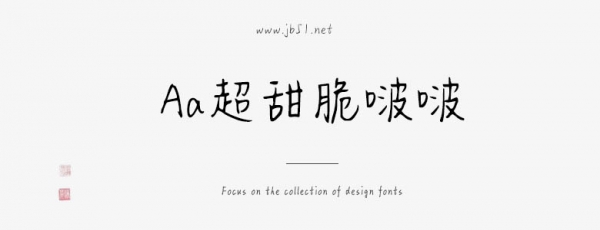
Aa超甜脆啵啵是一款不錯(cuò)的藝術(shù)字體,由Aa字庫出品,字體筆觸纖細(xì),書寫流暢,擁有字符數(shù)8028和字形數(shù)8008,具有很好的視覺感,適合應(yīng)用于藝術(shù)設(shè)計(jì)、平面宣傳設(shè)計(jì)、網(wǎng)頁設(shè)計(jì),書法字帖等領(lǐng)域,需要的朋友可以前來本站下載。